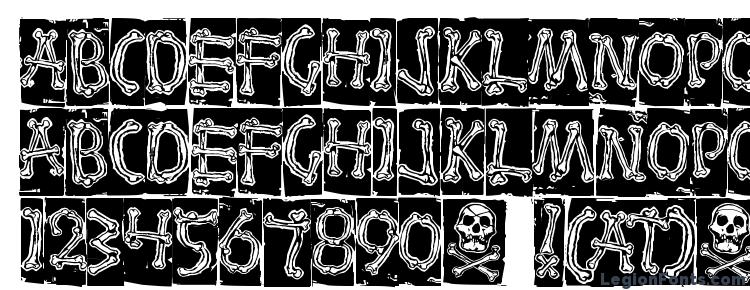
Пиратский шрифт русский: Русские шрифты | Шрифты онлайн
Журнал «Шрифт» • 10 шрифтов Владимира Ефимова
6 мая исполнилось 70 лет со дня рождения шрифтового дизайнера Владимира Ефимова (*6 мая 1949 †23 февраля 2012). Мы выбрали 10 шрифтов Владимира Венедиктовича и сопроводили их комментариями, которые он записал в 2010 году для выставки «Шрифтовых дел мастер» в Музее архитектуры. Позже они были помещены в небольшом каталоге, выпущенном компанией ParaType. Мы публикуем комментарии с небольшими сокращениями. Список начинается со шрифтов, которые не всегда связывались в сознании читателей с «академическим» стилем Владимира Ефимова. Между тем его кириллизации шрифтов Джонатана Барнбрука, студии «Эмигре» и других прогрессивных в 90-е годы словолитен и сегодня остаются мастерскими и смелыми проектами, о которых мы считаем нужным напомнить.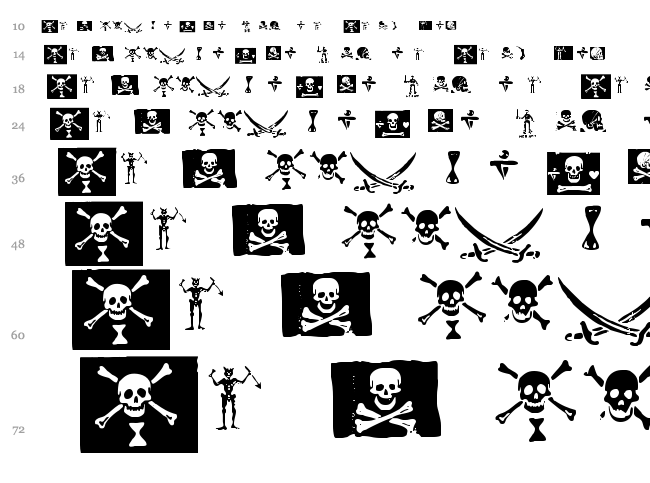
☛ ITC Avant Garde Gothic
Владимир Ефимов: «Авангард Готик — главный шрифт ITC, которым они безумно гордились. До того, как мы начали официальную работу над этим шрифтом, Максим Жуков уже заставлял меня рисовать eгo варианты для разных языков. Издательство „Мир“ выпускало литературу на русском и иностранных языках. Часть этих языков была восточная. Были издания для Индии, Афганистана и других стран. А поскольку я работал в лаборатории шрифтов особых графических форм, я был связан с восточными шрифтами. И Максим мне заказывал надписи в стиле Авангарда для индийской письменности деванагари, греческие, арабские.
У меня с этим Авангардом были уже какие-то личные отношения — он мне снился ночами. Я начал думать, как мне от него избавиться. Но тут открылся „Параграф“, и я туда перешёл, так как в отделе наборных шрифтов всё закончилось и закрылось.
У Любалина было в Авангарде нарисовано много лигатур, он хотел на новом уровне повторить то, что когда-то сделал Гутенберг. И мы решили, что раз уж выпускаем комплект начертаний в формате OpenТуре, то надо воспользоваться его преимуществом и добавить туда много-много лигатур. Мы сделали все лигатуры, которые нарисовал Любалин, а потом были сделаны кириллические аналоги, и получилось их очень много! Правда, я не знаю, зачем это нужно, но мало ли, вдруг кому-нибудь понадобится».
☛ Mason Sans
Владимир Ефимов: «Это был заказ известной пивной компании „Стелла Артуа“. У них был разработан фирменный стиль на основе Масона, и когда они открывали свое производство и представительство в России, им понадобился кириллический Масон.
Они заказали сетевому агентству разработку фирменного стиля, а те сами не стали делать кириллическую версию шрифта, а обратились к нам. Мне пришлось некоторое время этим заниматься. Этот шрифт позволяет проделывать с ним всякие модификации. Мне было довольно интересно с ним возиться: он настолько дик по своему основному решению в латинице, что мне нужно было найти ту же степень дикости в кириллице. У буквы А, например, было два варианта: одна — нормальная, треугольная (не очень нормальная, но почти), а у другой круглые бока и острая вершина, получается как будто боеголовка или снаряд. Это называется „оживальная форма“. Я сделал такие варианты ещё для Л и Д…
Когда я принёс уже довольно продвинутую нарисованную версию Масона нашему заказчику для утверждения, он, человек довольно молодой и на вид интеллигентный, сказал: вот какие шрифты были в рыцарские времена.
Тут я перепугался и сказал, что в рыцарские времена вообще-то готика была, а эта эклектика к рыцарским временам никакого отношения не имеет. В общем, мы друг друга поняли».
☛ Raleigh
Владимир Ефимов: «Был в Англии, в эпоху королевы Елизаветы, известный человек — Уолтер Рэлей (или Рейли). Фаворит королевы, личность замечательная, как и многие деятели шекспировских времён. Он был поэт и пират, организовывал экспедиции в Америку, воевал, писал историю Рима, сидя
в тюрьме в Тауэре. И, кстати, знаменит он настолько, что до сих пор в Тауэре его камера сохраняется в качестве музея — камера из двух комнат с балконом, там в общем-то неплохо было жить… Он был одним из лучших представителей эпохи королевы Елизаветы. Кончил он, правда, плохо — ему отрубили голову за государственную измену, в которой он был никак не повинен.
История этого шрифта достаточно запутанная, и сначала назывался он совершенно не так. Это был фирменный шрифт для Всемирной выставки 1969 года в Монреале, в Канаде, в одном начертании, и создал его дизайнер Карп Дэйр. Потом на его основе был сделан шрифт в двух начертаниях (прямое и курсив), названный Cartier. И опять же, я не уверен, что это было сделано по заказу этой самой знаменитой ювелирной фирмы. Его курсив был создан на основе старых и очень редких каллиграфических почерков, но в первоначальном шрифте, который был сделан для Всемирной выставки, курсива вообще не было, он был дорисован позже. Спустя какое-то время, в 1977 году, английский дизайнер Роберт Нортон на основе Cartier разработал этот самый шрифт в нескольких начертаниях — от сверхсветлого до сверхжирного.
☛ English 157
Владимир Ефимов: «Классический рукописный шрифт начала XIX века, называемый английским, или спенсерианским. В первом классе школы письму похожим шрифтом меня обучали на уроках чистописания. Мы писали металлическими перьями, макали их в чернильницу, все ходили в кляксах. Меня так и не научили толком. Пишутся они остроконечным стальным пером, позволяющим усиливать нажим, что делает их контрастными рукописными шрифтами, которые гармонировали с модными тогда Дидо и Бодони. Это имитация наборным способом рукописных шрифтов. English 157 — шрифт полусвязный: у него есть выходящие концы штрихов, а входящих концов нет. В основе его лежит знаменитый каллиграфический шрифт немецкого происхождения под названием Englische Schreibschrift („Английский рукописный шрифт“).
Я выбрал eгo сознательно, чтобы сделать кириллическую версию: такого типа шрифтов у нас не было, или были не очень качественные, с моей точки зрения.
☛ Kuenstler 480
Владимир Ефимов: «В 80-е годы в издательстве „Мир“ главным художником был Максим Жуков, и он пригласил меня делать разные шрифтовые работы. Мы делали книгу, которую заказала Ассоциация участников космических полётов. Это сборник космических фотографий удивительной красоты. Называлась она „Наш дом — Земля“. Это был перевод американского издания, и шрифт должен был быть как в оригинале. С текстовыми шрифтами это было тогда невозможно. Это сейчас их много, а тогда имелись только Таймс и Гельветика, гарнитура Литературная как-то не подходила. Но хотя бы переплёт и титул должны были соответствовать оригиналу. И мне заказали такую вот работу.
Владимир Ефимов о работе над кириллической версией шрифта Kuenstler 480. 2010 год.
Некоторое время у меня ушло на то, чтобы опознать шрифт, так как там нигде не было написано его названия. Потом я его нашёл в каталоге, оказалось, что это Трамп Медиеваль. Я его переснял с увеличением, перерисовал на кальку. Никто не знал, прописными нужно было делать надпись или строчными, поэтому я сделал и то и другое. Это был первый вариант шрифта, и он потом никуда не пошёл. Современный вариант я сделал уже позже в „ПараТайпе“ на основе цифровой битстримовской версии».
☛ ImagoВладимир Ефимов
: «Гюнтер Герард Ланге разработал для Бертольда множество шрифтов — варианты классических гарнитур, перерисованные для фотонабора, и оригинальные.
Imago — его оригинальный шрифт. Изначально он был разработан в меньшем количестве начертаний, но в 2000 году в Чикаго было сделано жирное начертание, в 2005 году — нормальное, которого в оригинальном фотонаборном шрифте не было. В результате гарнитура получилась естественно возрастающей по насыщенности, без рывков от светлых начертаний к жирным.В каждом начертании этой гарнитуры есть капитель, что для меня было довольно странно. Не очень понимаю, зачем нужна капитель в гротеске, особенно в наклонных начертаниях. Однако теперь в шрифтовом дизайне принято давать типографу как можно больше возможностей, а уж воспользуется он ими или нет — это его дело».
☛ Octava
Первоначальная русская версия в трёх начертаниях под названием Scriptura Rossicа (1996) была заказана Российским библейским сообществом.
Владимир Ефимов: «Эскизы шрифта были показаны в библейском сообществе для утверждения, после чего в каждом начертании были доработаны недостающие знаки и построены рабочие файлы шрифта.
Они были переданы заказчику, который провёл своё тестирование в условиях вёрстки реального издания. Несколько полос из Библии были набраны новым шрифтом с разными установками: разными кеглями, при различных значениях интерлиньяжа, комбинациях начертаний и т. д. После последних корректировок и технической обработки всех знаков (хинтования) шрифт был построен уже в окончательной версии и передан заказчику».
☛ Гарнитура Лазурского
Владимир Ефимов: «Как пишет сам Лазурский в своих воспоминаниях, eгo работа над наборным шрифтом началась в 1957 году в Отделе редких книг Библиотеки им. Ленина (сейчас Российская государственная библиотека), где он вручную копировал латинские шрифты эпохи Возрождения. На основе этого материала он затем стал искать форму знаков будущей гарнитуры Лазурского. К сожалению, Лазурский не оставил подробного описания этапов этого процесса.
По иллюстрациям, помещённым в его книге, видно, как от прилежных карандашных копий исторических образцов он перешёл к рисованию собственных буквенных форм.
Эскизы Вадима Лазурского к первому типографскому шрифту, позже названному гарнитурой Лазурского. 1957. Из мемуаров художника „Путь к книге“ (М.: Книга, 1985).
Среди множества эскизов этого периода есть несколько рисунков, свидетельствующих о том, как художник, вынужденный по техническим требованиям перейти к резко увеличенному масштабу букв, должен был определить стиль и форму будущих наборных знаков. Эти рисунки букв поражают своей удивительной экспрессией и современностью: увеличенные копии отпечатков текстовых шрифтов, с присущим им ростиском краски и погрешностями ручного рисования, в крупном размере приобрели неожиданные графические качества. За их внешней суровостью чувствуется железная конструкция и пятисотлетняя традиция шрифтового дизайна.
Именно так и должен выглядеть в таком размере настоящий текстовый шрифт, и первая аналогия, приходящая в голову при виде этих эскизов, — это шрифты Уильяма Двиггинса, а также шрифт IТС Galliard Мэтью Картера, который опирался на шрифты Робера Гранжона».
☛ Didona
Владимир Ефимов: «Для книги Максима Жукова про Большой театр я сделал эскизы. Но затем они долго лежали без движения. Потом мне стало обидно, что они лежат, и захотелось их использовать. Но когда я собрался делать нормальный шрифт, я понял, что шрифт такой контрастности и с такими немного диковатыми формами у нас никто не выдержит. И тогда я волевым решением взял и увеличил вдвое толщины тонких штрихов, то есть в эскизах толщина штриха была 1 мм, а стала 2 мм. И из этого тогда получился шрифт Дидона.
Владимир Ефимов о том, как делался шрифт Дидона.
2010 год.
В сущности, это не просто шрифт, а моё отношение к шрифту в те времена. И не просто отношение, а отношение довольно ехидное. Там есть некоторые вещи, которые „я себе позволил“. Вот, например, 4 и 7 — это реально существующие цифры, они подсмотрены и срисованы, но вот такой Д тогда ещё ни у кого не было. Или капля у буквы З — в этих знаках, формах есть внутреннее ехидство, это не просто переработка известной формы, а моё личное, немного ироничное отношение к ним, здесь есть элемент игры. В нормальном шрифте я бы такого не сделал, то есть сделал бы, но немного не так, а более серьёзно».
☛ Kis
Владимир Ефимов: «Матрицы этого шрифта были найдены в начале ХХ века, тогда же был отлит с этих матриц шрифт. Сначала его авторство приписывали Антону Янсону, но только в 50-е годы ХХ века обнаружили, что это Николай Киш. Я давно на него смотрел, и мне, конечно, хотелось сделать кириллическую
версию, потому что, по-моему, это один из самых красивых латинских шрифтов.
Я попробовал его рисовать, получилось, конечно же, не сразу. Уже в современные времена „ПараТайп“ заключил договор с американской фирмой Bitstream, по которому мы имеем право делать кириллические версии их шрифтов. А у них в библиотеке был шрифт Киш, и поскольку я уже давно начал его рисовать, то эта работа досталась мне.
Владимир Ефимов о разработке кириллической версии шрифта Kis. 2010 год.
Это было связано ещё с тем, что я всегда не понимал Петровскую реформу, гражданский шрифт, который получился такой достаточно странный, и я решил, что надо было взять самый лучший латинский шрифт и уже к нему подбирать варианты кириллических знаков. И я выбрал шрифт Киш, так сказать, для повторения Петровской реформы на современном уровне, чтобы сделать формы наших букв более человеческими».
Создателей мультика My Little Pony судят за пиратский шрифт / Хабр
Компания-разработчик шрифтов Font Brothers подала в суд на производителя игрушек и настольных игр Hasbro за использование одного из фирменных шрифтов без разрешения. Согласно жалобе Font Brothers, компания Hasbro отказалась платить лицензионные отчисления и продолжала использовать шрифт в товарах линейки My Little Pony (в русском переводе мультик называется «Дружба — это чудо»).Конфликт возник из-за шрифта Generation B, который создал дизайнер Гарольд Лонер (Harold Lohner). В судебном иске (pdf) сказано, что шрифт использовался в линейке игрушек и сувениров My Little Pony, а также в мультсериале и рекламных материалах Hasbro, чему есть доказательства. К исковому заявлению прилагаются образцы буклетов и фотографии игрушек с контрафактным шрифтом.
Доказательства довольно убедительные, тем более что в исходном коде HTML-страниц на веб-сайте Hasbro прямо указано использование шрифта Generation B.
Неизвестно, почему Hasbro отказалась покупать лицензию на использование шрифта. Возможно, запрошенная сумма оказалась слишком высокой.
По оценке экспертов, потенциальный ущерб Font Brothers может составить миллионы долларов. Вдобавок, Font Brothers имеет право потребовать уничтожения всех товаров и материалов, где используется пиратский шрифт.
События в мультфильме My Little Pony разворачиваются в вымышленной стране Эквестрия, населённой пони. Главная героиня — единорог по имени Сумеречная Искорка (Twilight Sparkle), которая целые дни проводит за книгами, не уделяя ни минуты общению с другими пони. Её наставница принцесса Селестия даёт ей задание — найти настоящих друзей. Героиня и её помощник дракончик Спайк отправляются в Понивиль, где встречают преданную друзьям Радугу Дэш, щедрую Рарити, честную Эпплджек, добрую Флаттершай и всегда веселую Пинки Пай.
Целевая аудитория мультсериала — девочки от 4 до 7 лет.
Слева направо: Пинки Пай, Рарити, Радуга Дэш, Сумеречная Искорка, Эпплджек и Флаттершай
Тара Стронг, Сумеречная Искорка
Получается, что маленькие девочки 4-7 лет, которые смотрят мультсериал и покупают игрушки с пони, тоже пользуются пиратской продукцией.
Шрифт и контент | Блог Смартпринт.рф
Часто текст расценивают, как контент (смыслы) и забывают о его роли, как о графическом элементе (выбор шрифта). А между тем, шрифт воздействует на подсознание не меньше, чем цвет (следовательно, и на восприятие рекламного материала).
Сила смыслов должна быть подкреплена силой визуализации
Вопросы, которые возникают при работе с шрифтами:
- Как выбрать шрифт?
- Какие параметры необходимо учитывать, чтобы подобрать шрифт для макета?
- Где найти бесплатные шрифты?
Шрифт — инструментом визуальной коммуникации бренда с потребителем.
Каждый шрифт имеет свое воздействие на подсознание, задает настроение во время чтения текста.
Прямые вытянутые шрифты отлично подходят для рекламы услуг и продукции, где нужно передать деловое настроение, но не уместны для необычных, уникальных товаров, которым нужно выделиться на фоне конкурентов.
Строгие квадратные шрифты призваны настроить человека на серьезность предоставленной информации.
Где используют:
- реклама промышленных товаров,
- продвижение технологий,
- для социальной рекламы.
Округлые шрифты передают чувство комфорта и уюта. Ассоциируются с добрым отношением бренда к потребителям.
Если у продукта основная аудитория девушки и женщины, то лучше использовать наклонные шрифты, они ассоциируются с легкостью и красотой.
Где используют: салоны красоты, магазины одежды, косметические бренды.
Рукописные шрифты — это попытка передать дружелюбие и близкие отношения.
Такие шрифты вызывают чувство доверия и придают большую достоверность информации.
Где используют:
- дизайн для адвокатских и консалтинговых услуг,
- реклама врачебной практики,
- для пригласительных,
- при проведении политических PR-акций.
На шрифты часто не обращают внимания. У нас на Смартпринт был случай, когда после масштабирования макета из формата А4 до формата до А5 некоторые текстовые элементы наехали друг на друга.
Мы предложили заказчику доработать макет или отправить специалисту допечатной подготовки шрифт, который использован в файле. На это заказчик ответил: «Поставьте там какой-нибудь свой шрифт, мне главное, чтобы смысл не изменился.
Этот пример очень хорошо демонстрирует отношение к шрифту.
Давайте разбираться, чем шрифты отличаются и для каких целей подходят.
Есть две основные группы шрифтов — антиквы и гротески. Антиквы — это шрифты с засечками, гротески — без засечек.![]()
Для длинных текстов лучше использовать шрифт с засечками. Так текст будет легче читать.
Шрифты без засечек, то есть гротески, окружают нас повсюду — они используются в логотипах, рекламе, упаковке и даже в книгах.
При подборе шрифта важно руководствоваться не только аргументом «нравится/не нравится», но и учитывать сферу деятельности. Нельзя использовать один и тот же шрифт и для рекламы детских товаров, и для продвижения услуг юридической фирмы.
Отдельная тема — сложные/необычные шрифты, они хороши для названий заголовков, но не для основного текста, иначе он просто станет не читаемым.
Каждый шрифт был сделан для решения определенной задачи, это стоит учитывать при его использовании.
При выборе шрифта нужно брать во внимание контекст. Не используйте готические шрифты для рекламы пекарни, а славянскую вязь — для логотипа фитнес-клуба.
Есть платные и бесплатные шрифты. Для крупного проекта есть смысл заморочиться на покупку или даже на разработку шрифтовой гарнитуры специально под ваш проект, но если вам нужно подобрать шрифты для брошюры или буклета, то можно воспользоваться бесплатными вариантами.
Бесплатный, не значит пиратский.
Это может быть просто бесплатный шрифт, работа начинающего шрифтовика или любителя, акция в магазине или пробная версия.
Где искать бесплатные шрифты:
Free Design : Отборные Бесплатные Шрифты
BaseFonts. Отборные кириллические шрифты
- Студии, разрабатывающие шрифты
На своих сайтах они продают шрифты собственного производства, но, кроме этого, часто можно найти 1-2 бесплатных шрифта, например:
Russianfonts
Typefaces of the temporary state
Free Fonts Project
Fontfabric
У многих платных шрифтов часто есть 1-4 бесплатных начертания.
- Отдельные дизайнеры
- Сайты с подборками
Вариант удобен тем, что в нём уже собраны многие шрифты из предыдущих пунктов в одном месте. Но есть и минус: в подобных подборках могут быть и пиратские шрифты.
https://graphicsland.ru/mark/cyrillic/
https://shriftkrasivo.
ru/category/cyrillic/. - Поиск на Behance
Достаточно ввести в поиск «Cyrillic free» и посмотреть варианты.
Похожие статьи:
Шрифт как элемент фирменного стиля
Принимая во внимание деятельность фирмы ParaType, разговор пойдет преимущественно о шрифтах. Очень хочется думать, что читатели понимают, что шрифт появляется не «с дискетки». Его делают художники, поэтому как и любое произведение искусства, будь то графический дизайн или фотография, шрифт является авторским произведением.
Начнем с простых примеров того, как различные фирмы подходят к решению вопросов поддержания единого фирменного стиля и ситуаций, в которые в связи с этим попадают отечественные фирмы и представительства иностранных компаний в России.
Первым хотелось бы упомянуть Сбербанк Российской Федерации, который использует хорошо узнаваемый всеми нашими гражданами шрифт ITC Benguiat (назван по фамилии автора). Слова «Сберегательный банк» на всех бланках, буклетах, сберкассах на всевозможных языках написаны этим шрифтом.
Долгое время Сбербанк использовал нелегальную русифицированную версию этого шрифта.
Под «нелегальной версией» в данном случае подразумевается следующее: с пиратского диска берется шрифт, содержащий символы латиницы. Некий «местный дизайнер» дорисовывает кириллические символы, не согласуя работу с владельцем оригинала. Полученный таким образом шрифт получает широкое распространение на тех же пиратских дисках. И вот некое рекламное агентство или дизайн-бюро разрабатывает фирменный стиль, не обращая внимание на происхождение шрифта. Шрифт становится фирменным и используется в логотипе. Тем самым наносится серьезный урон репутации клиента, так как хоть и существует техническая возможность тиражировать шрифты, представленные в компьютерных форматах, это не отменяет необходимость соблюдения Закона РФ «Об авторском праве и смежных правах».
И вот в Сбербанке, спустя какое-то время, возникла необходимость проверить все элементы фирменного стиля с точки зрения соблюдения авторских прав.
Нужно было сделать следующее: первое — приобрести право использовать латинскую часть шрифта, второе — русифицировать в России латиницу, то есть, создать кириллицу. И третье — приобрести лицензии на установку шрифта на определенном количестве (более ста) компьютеров для работы во всех филиалах.
Второй пример. Американская фирма Compaq (один из лидеров компьютерного мира), имеющая свой фирменный стиль, обязала сотрудников российского офиса оформлять документацию на русском языке в соответствии с системой корпоративной идентификации. В эту систему входил шрифт Тезис (автор Лукас де Грот, довольно известный немецкий дизайнер). Фирма имела права на латиницу. Была создана кириллица и приобретена простая лицензия на использование кириллицы для издательской деятельности и выпуска техдокументации.
Третий пример.* Концерн Фольксваген на билбордах и в печатной рекламе автомобиля VW (не Аudi) использовала шрифт Futuris Demi. Можно сравнить журналы для западного читателя и российского: тексты в них набраны разными шрифтами.
В западных изданиях используются шрифты VAG Rounded (фирменный шрифт Фольксвагена) и Futura.
Не найдя похожего на VAG Rounded кириллического шрифта, компания просто исключила его из рекламы, а вместо Futura использовала ближайший аналог — шрифт Futuris. Оба действия вызывают удивление, т.к. в масштабах рекламной кампании автомобильной фирмы изготовить любой фирменный шрифт на заказ вполне реальная задача, что же касается шрифта Futura, то существуют официальные кириллические версии этой гарнитуры, созданные фирмой ПараТайп.
Первый случай, пожалуй, наиболее общий и наиболее серьезный. Речь идет о большой организации с развитой системой филиалов, с достаточно жесткими требованиями к системе корпоративной идентификации. Для банка фирменный стиль играет особую роль. Надпись «Сбербанк Российской Федерации» должна быть едина для всех документов и для всех филиалов, как в России, так и за рубежом.
Второй случай с переводом фирменной документации на другие языки — более частный, но не менее интересный.
Обратите внимание на то, что в паспортах бытовой техники, выпущенной 3-5 лет назад, уже переведенных на русский язык (это может быть 10 языков), все блоки набраны разными шрифтами: латиница одним, кириллица другим, иная группа языков — третьим. Если же вы возьмете современную техническую документацию солидной фирмы, то все чаще и чаще весь документ оформлен в едином формате, набран единым шрифтом на всех языках и имеет некий унифицированный вид. Для системы корпоративной идентификации это, безусловно, имеет значение.
Третий случай интересен как пример международной рекламной кампании, проводимой сетевыми агентствами. Он аналогичен первому и второму, является массовым, но «работает» в период проведения конкретной рекламной кампании. Если рекламная кампания имеет интернациональный характер, очень важно для сохранения визуального ряда использовать в разных странах, для разных языков, один и тот же набор шрифтов. В компании Мерседес данное требование выполняется повсеместно. Вся реклама Мерседеса сверстана c использованием одного шрифта, и в телефонных справочниках, и в журналах.
Можно привести примеры использования фирменного шрифта транснациональными табачными компаниями или фирмами, торгующими продуктами питания. Однако, в подавляющем большинстве случаев, на территории бывшего СССР фирменный стиль в рекламных кампаниях не соблюдается. Макеты рекламы сохраняют слоган, логотип и видеоряд, но, к сожалению, шрифт подбирают по критерию «похож — не похож», что говорит о недостаточной профессиональной подготовке сотрудников рекламных агентств. Подобные решения должны принимать профессионалы, так как каждый шрифт соответствует вполне определенному стилю и направлению в графическом дизайне, и даже «маленькая» ошибка может полностью разрушить первоначальную идею оригинального дизайна. «Специалистам», которые считают, что все шрифты одинаковы, напомню, что для европейца все китайцы имеют одинаковое выражение лица и абсолютно похожи друг на друга.
Когда мы говорим о фирменном стиле или о системе корпоративной идентификации, то имеем в виду целый комплекс понятий. И шрифт является одной из составляющих, наравне с сеткой, фирменным цветом, логотипом.
Какие трудности нас здесь ждут?
Начнем с чисто технологических. Международные рекламные кампании, как правило, приходят к нам с запада. На западе коммерческих шрифтов (по каталогам) более 15 тысяч. Причем, западные фирмы, наверное, не зря тратят такие большие деньги на рекламу и консультантов. Очень часто они используют модные шрифты, которые появились 2-3 года назад, и существуют, как правило, только в латинице. Это большая проблема для нашего рынка. Не только потому, что необходимо подбирать кириллицу. В российских регионах такая реклама идет на национальных языках, и очень часто проблема белорусского, украинского, татарского, казахского языка — это проблема московского рекламного агентства. И надо обращать на это внимание. Если не получается сделать «как в латинице», надо постараться подобрать близкий шрифт. Здесь очень важно обратиться к специалисту, профессионалу.
К примеру, шрифт, используемый в рекламной кампании «Ингосстраха», существует для украинского и большинства других языков.
Но при проведении рекламной кампании по России в целом, местные рекламисты в Башкирии и Татарстане вряд ли обратят внимание на то, что шрифт именно Futuris, а не Helvetica, Pragmatica или Arial. На это обязательно должен обратить внимание менеджер, составляя контракт. Подрядчику фирменный цвет, набор фотографий, текст, шрифт должны передаваться единым комплектом. Эти требования должны быть изложены соответствующим образом по всей цепочке договоров.
Здесь могут быть совершенно неожиданные и чисто утилитарные проблемы. Если шрифт заменен на похожий, может просто не сохраниться верстка при фотонаборе. При замене одного шрифта другим, текст просто «сползет» (если речь идет о десяти символах) или будет переверстан (если о нескольких предложениях). У другого шрифта другая ширина, другая высота символа. И возможно, что если и не будет утерян смысл, то некий замысел, задуманный дизайнером, вполне может быть нарушен.
Сегодня в рекламе товаров народного потребления, автомобилей, продуктов питания и т.
д., как правило, стараются избегать характерных шрифтов, если они не являются частью товарного знака. Пример — тот же, достаточно нейтральный, Futura в рекламе Фольксвагена. Современный, конструктивистский, он был моден в начале 80-х и широко используется в настоящее время. Решение, позволяющее сделать замену,если нет прямого аналога шрифта. Очень часто западная реклама (я обращаю внимание на то, что это один из критериев высочайшего профессионализма дизайнера) сделана так, что шрифт можно заменить другим без потери смысла и задумки дизайнера. Ну, будет не так красиво. Да, профессионалы заметят. Но это вполне допустимо. Дизайн шрифта может не нести смысловой нагрузки, если он не привязан к изображению временем, дизайном, стилем и т.д.
Здесь есть минусы. Говорят, интернациональные рекламы безлики, в них нет «изюминки». Но они очень профессиональны, их сложно испортить. Это удобно для рекламы автомобилей, магнитофонов, жвачки, напитков. Для системы корпоративной идентификации ситуация прямо противоположная — шрифт должен нести смысловую нагрузку.
Речь идет, прежде всего, о годовых отчетах и иной документации банков, страховых компаний, других финансовых организаций.
Если ваша задача — узнавание компании, создание некоего образа в документах: отчетах, бланках, визитных карточках, то самый важный принцип — соблюдение меры. В «серьезной» документации шрифт, когда шрифт несет еще и содержательную функцию, как правило, используют шрифты, которые ассоциируются с богатством, респектабельностью, например, классические шрифты типа Garamond или Baskerville. Это действительно солидные шрифты, перед которыми хочется снять шляпу. Они очень непросты в использовании и выдвигают дополнительные требования к дизайну в целом. Это требует от автора дизайн-проекта дополнительных знаний по истории и типографике. Но, может быть, эти шрифты правильнее использовать в альбомах по искусству?
В архитектуре количество золота, лепнины, резной фасад — признак определенной эпохи, стиля. И если уж вы построили екатерининский дворец, то и ходите в парике и парче. А если уж приехали на современном спортивном автомобиле и у вас особняк из финских материалов, то и шрифт лучше не екатерининской эпохи взять, а современный, чуть агрессивный, что не мешает ему быть модным и респектабельным. Большинство ошибок современного полиграфического дизайна как раз связано с полным несоответствием выбранного шрифта характеру и содержанию издания.
Трудно соблюсти всю линию фирменного стиля, включая интерьер помещений и униформу сотрудников. Необходимо выдерживать в стиле все элементы, включая и цветовую гамму.
И еще архитектурный пример — С.-Петербург. Желтые здания имеют дизайн своего времени. Зеленоватые — своего. Их не перекрасишь. Если вы построили особняк и покрасили его в голубой цвет — делайте лепнину. А если стиль более конструктивистский, хотите Смольный, — покрасьте его в желтый цвет.
Наверное, не нужно подстраивать весь фирменный стиль под здание, в котором работаешь, но иметь в виду простейшие правила необходимо. Ведь очень странно смотрится шрифт стиля модерн (первой половины 20 века) на екатерининском особняке. Если речь идет о вывеске «Трактир» или «Пивная», то с этим еще можно смериться, но если о наименовании банка либо представительства некоей западной компании, — то это вызывает улыбку. К тому же часто в рекламе используется вид главного офиса компании. И стиль рекламы, в этом случае, должен соответствовать парадному подъезду. Вывеска — архитектуре подъезда.
Не нужно быть профессором графики или преподавать оформление книги, чтобы понимать: шрифт, если он используется в наружной рекламе — это такая же часть среды, как и архитектура. Если же он используется на бумаге, то это такой же равноправный элемент, как все остальное, что помещено на этой же странице.
Если об этом помнить и стараться привести все компоненты в соответствие, то сам собой выстроиться стиль. Если он не выстраивается или что-то не получается, значит, надо что-то изменить. Как правило, шрифт поменять легче, чем все остальное. Если уже существует фотография президента в рыцарских доспехах, то ничего с ней поделать нельзя (как в прямом, так и в переносном смысле). И если миллионы уже затрачены на реконструкцию подъезда в первозданном виде. Шрифт является, как правило, менее критичной частью.
Не надо бояться современных шрифтов, современного дизайна. Только важно соблюсти в фирменном стиле некую преемственность и сбалансированность звучания. Я видел хорошие фирменные стили, построенные на швейцарской типографике: Гельветика и т.п. — все очень строго. Это не очень модно, не очень современно. Сейчас так не делают. Но если это было сделано в свое время продуманно, то здесь есть и преимущества: фирменный стиль показывает, когда он был создан и как долго существует. Он служит дополнительным фактором в выполнении поставленной задачи — отразить, например, незыблемость и надежность банка.
Одна компания может использовать несколько шрифтов с разными целями: один — для официальных документов, нормированный, гостированный. Другой может быть массово тиражируем, им можно печатать техническую документацию. Третий может представлять собой комплект для текущей рекламной кампании. Шрифты не обязательно должны быть сверхмодными и выдающимися. Они должны соответствовать поставленной задаче.
На западе фирменные шрифты имеют не только солидные компании, но и у государственные департаменты. Заказные шрифты есть у газет, которые стараются идентифицировать себя в общем поле. Для коммерции очень важно, когда в огромном развале газет можно мгновенно отличить то или иное издание по заголовку, по набору, не будучи специалистом. Нам до этого далеко. Но к использованию уникального заказного шрифта, как элемента фирменного стиля, мы приходим. Пример тому — Сбербанк. Многие просят изменить в шрифте несколько букв, чтобы стиль стал фирменным, и его можно было идентифицировать.
Есть хорошие примеры того, как надо работать со шрифтами. «Коммерсант Дейли» несколько раз менял шрифт. Поиск был достаточно длительным. Подзаголовки сейчас набираются фирменным шрифтом Free Set — аналогом шрифта Frutiger «живого классика» типографики Андриана Фрутигера. Это современный открытый гротеск, очень хорошая альтернатива Гельветики. Хотя есть уже новые гротески, он останется современным еще лет десять-двадцать. В качестве заголовочного шрифта используется Swift (это антиква с тяжелыми рублеными засечками, автор Унгер). Нигде больше как в «Коммерсант Дейли» он не используется. Сейчас делается новая версия Swift, который будет массово тиражироваться и продаваться всем желающим.
Еще один, на этот раз вопиющий пример. Замечательная, своевременная акция «Знак рубля». Молодцы! Сто баллов! Конкурс проводили профессиональные журналисты, дизайнеры. Но почему в отборочной комиссии не было ни одного шрифтовика? Из Академии печати, из Союза дизайнеров, откуда угодно. Из-за границы, наконец. В числе выбранных знаков есть буква «Ъ» из гарнитуры Лазурского. Поскольку знак рубля — шрифтовой знак (как доллар, как иена, фунт), получается, что твердый знак гарнитуры Лазурского нужно вставить во все существующие шрифты. Понятно, что знак рубля будет использоваться вместе с цифрами, что его нужно поставить во все, имеющие хождение шрифты. Этот знак рубля будет рисоваться для гротеска, антиквы, декоративного шрифта. Он должен соотноситься со знаком иены, доллара, форинта, флорина, и др. Только один знак из вышедших в финал сделан профессионально, дизайнером-шрифтовиком. Остальных «врачи не лечили».
Хороших справочников на русском языке, где есть обзоры шрифтов, нет, зато есть десятки на английском, Это любая книга по типографике (одной из лучших я считаю книгу Эмиля Рудера «Типографика»). Но в то же время компетентные грамотные люди, профессионально занимающиеся рекламой, не пытаются самостоятельно выводить пленки. Они идут в фотонаборный центр и консультируются, какой должна быть верстка, чтобы она была технологична и хорошо выводилась на фотонаборе. Они консультируются с представителями типографий, какой должен быть цвет, чтобы он хорошо напечатался и на мелованной бумаге, и на простой офсетной. То же самое со шрифтом. Не надо бояться проконсультироваться. Есть очень хорошие дизайнеры, которые в этом разбираются. Есть просто художники-шрифтовики. Есть преподаватели в полиграфическом институте. Этих людей немало. Их несложно найти. Любой профессиональный дизайнер-полиграфист скажет вам, что дизайн шрифта — это «высший пилотаж».
Можно сколь угодно долго рассказывать о правилах построения кириллицы, это целый мир. Но лучше, если вам поможет человек, который этим занимается профессионально. Если вам не понравился один консультант, идите к другому, это легче, чем с врачом. Но если и второй, и третий говорят одно и то же, нужно задать себе вопрос: а прав ли я?
По информации dp-foto.ru
Автор:
☠ — Череп и кости Эмоджи: U+2620
пиратский флаг, смерть, опасность
U+2620
Emoji
Отображение этого Emoji в разных системах
Значение Эмоджи
Череп с двумя скрещёнными костями означает смерть или смертельную угрозу. Такой символ предупреждает о минном поле или химическом заражении. Пираты рисовали нечто подобное на своём флаге и называли его «весёлый Роджер».
Символ «Череп и кости» был утвержден как часть Юникода версии 1.1 в 1993 г. и был добавлен в Эмоджи версии 1.0 в 2015 г.
Этот текст также доступен на следующих языках: English;
Свойства
| Версия | 1.1 |
| Блок | Разные символы |
| Тип парной зеркальной скобки (bidi) | Нет |
| Композиционное исключение | Нет |
| Изменение регистра | 2620 |
| Простое изменение регистра | 2620 |
Злое или недовольное лицо
Кодировка
| Кодировка | hex | dec (bytes) | dec | binary |
|---|---|---|---|---|
| UTF-8 | E2 98 A0 | 226 152 160 | 14850208 | 11100010 10011000 10100000 |
| UTF-16BE | 26 20 | 38 32 | 9760 | 00100110 00100000 |
| UTF-16LE | 20 26 | 32 38 | 8230 | 00100000 00100110 |
| UTF-32BE | 00 00 26 20 | 0 0 38 32 | 9760 | 00000000 00000000 00100110 00100000 |
| UTF-32LE | 20 26 00 00 | 32 38 0 0 | 539361280 | 00100000 00100110 00000000 00000000 |
О переводах и технических трудностях… (Выпуск 1) — Офтоп на DTF
Судя по результатам первого-последнего выпуска, вам понравилось, дорогая аудитория. Ну-с, как и обещал, мы начнём по порядку.
Небольшой дисклеймер: не удивляйтесь разнице в структуре и стиле. Всё же выпуски первые и я только начинал экспериментировать. А теперь — приятного чтения!
P.S. Данный выпуск был опубликован впервые 25-го мая 2017-го.
{«id»:13880,»url»:»https:\/\/dtf.ru\/flood\/13880-o-perevodah-i-tehnicheskih-trudnostyah-vypusk-1″,»title»:»\u041e \u043f\u0435\u0440\u0435\u0432\u043e\u0434\u0430\u0445 \u0438 \u0442\u0435\u0445\u043d\u0438\u0447\u0435\u0441\u043a\u0438\u0445 \u0442\u0440\u0443\u0434\u043d\u043e\u0441\u0442\u044f\u0445\u2026 (\u0412\u044b\u043f\u0443\u0441\u043a 1)»,»services»:{«vkontakte»:{«url»:»https:\/\/vk.com\/share.php?url=https:\/\/dtf.ru\/flood\/13880-o-perevodah-i-tehnicheskih-trudnostyah-vypusk-1&title=\u041e \u043f\u0435\u0440\u0435\u0432\u043e\u0434\u0430\u0445 \u0438 \u0442\u0435\u0445\u043d\u0438\u0447\u0435\u0441\u043a\u0438\u0445 \u0442\u0440\u0443\u0434\u043d\u043e\u0441\u0442\u044f\u0445\u2026 (\u0412\u044b\u043f\u0443\u0441\u043a 1)»,»short_name»:»VK»,»title»:»\u0412\u041a\u043e\u043d\u0442\u0430\u043a\u0442\u0435″,»width»:600,»height»:450},»facebook»:{«url»:»https:\/\/www.facebook.com\/sharer\/sharer.php?u=https:\/\/dtf.ru\/flood\/13880-o-perevodah-i-tehnicheskih-trudnostyah-vypusk-1″,»short_name»:»FB»,»title»:»Facebook»,»width»:600,»height»:450},»twitter»:{«url»:»https:\/\/twitter.com\/intent\/tweet?url=https:\/\/dtf.ru\/flood\/13880-o-perevodah-i-tehnicheskih-trudnostyah-vypusk-1&text=\u041e \u043f\u0435\u0440\u0435\u0432\u043e\u0434\u0430\u0445 \u0438 \u0442\u0435\u0445\u043d\u0438\u0447\u0435\u0441\u043a\u0438\u0445 \u0442\u0440\u0443\u0434\u043d\u043e\u0441\u0442\u044f\u0445\u2026 (\u0412\u044b\u043f\u0443\u0441\u043a 1)»,»short_name»:»TW»,»title»:»Twitter»,»width»:600,»height»:450},»telegram»:{«url»:»tg:\/\/msg_url?url=https:\/\/dtf.ru\/flood\/13880-o-perevodah-i-tehnicheskih-trudnostyah-vypusk-1&text=\u041e \u043f\u0435\u0440\u0435\u0432\u043e\u0434\u0430\u0445 \u0438 \u0442\u0435\u0445\u043d\u0438\u0447\u0435\u0441\u043a\u0438\u0445 \u0442\u0440\u0443\u0434\u043d\u043e\u0441\u0442\u044f\u0445\u2026 (\u0412\u044b\u043f\u0443\u0441\u043a 1)»,»short_name»:»TG»,»title»:»Telegram»,»width»:600,»height»:450},»odnoklassniki»:{«url»:»http:\/\/connect.ok.ru\/dk?st.cmd=WidgetSharePreview&service=odnoklassniki&st.shareUrl=https:\/\/dtf.ru\/flood\/13880-o-perevodah-i-tehnicheskih-trudnostyah-vypusk-1″,»short_name»:»OK»,»title»:»\u041e\u0434\u043d\u043e\u043a\u043b\u0430\u0441\u0441\u043d\u0438\u043a\u0438″,»width»:600,»height»:450},»email»:{«url»:»mailto:?subject=\u041e \u043f\u0435\u0440\u0435\u0432\u043e\u0434\u0430\u0445 \u0438 \u0442\u0435\u0445\u043d\u0438\u0447\u0435\u0441\u043a\u0438\u0445 \u0442\u0440\u0443\u0434\u043d\u043e\u0441\u0442\u044f\u0445\u2026 (\u0412\u044b\u043f\u0443\u0441\u043a 1)&body=https:\/\/dtf.ru\/flood\/13880-o-perevodah-i-tehnicheskih-trudnostyah-vypusk-1″,»short_name»:»Email»,»title»:»\u041e\u0442\u043f\u0440\u0430\u0432\u0438\u0442\u044c \u043d\u0430 \u043f\u043e\u0447\u0442\u0443″,»width»:600,»height»:450}},»isFavorited»:false}
Вспоминая бурную молодость и расцвет моей переводческой деятельности, не могу не отметить: по большей части они строились на одном энтузиазме. Однако сейчас, в пору занятности и отсутствия достаточного свободного времени, энтузиазм погас, но любовь к переводам не остыла. Сейчас же я готовлюсь к довольно интересному проекту, и хотелось бы поведать вам о «трудностях перевода» не в плане разница локализаций, а в плане самого процесса. В качестве примеров возьму два проекта: Resident Evil Zero (+HD Remaster) и Winx Club (2006-го).
Феечки Винкс могут задать жару…
Начнём с более простого. Игру по мультсериалу «Клуб Винкс» издала Konami в 2006-ом. Как не странно, игра было довольно неплоха. Это хороший (для игры по детскому мультфильму) экшен-платформер, где исследование сменяется платформингом, платформинг боями (Боевая система строится на уклонениях, захвате цели и стрельбе), а бои снова исследованием. Но в этой статье нас интересует не сама игра, а… «Внутренний мир» или её файлы. Я не буду разбирать сейчас версию для PS2 (Однако в ней я копался, пытаясь выудить ролики, но об этом позже). Наша цель – версия для PC. Итак. Что же нам надо искать в игре с точки зрения перевода?
Шрифт.
Это нужно смотреть и искать в первую очередь, поскольку выудить один текст недостаточно. Если вы хотите сделать качественный перевод, то придётся напрячься и вставить в шрифт русский алфавит. Если же по каким-то причинам это не получается, то некоторые одарённые личности обходятся тем методом, которые придумали пираты в 90-ые/начале нулевых – замена латиницы на русский шрифт, в результате чего текст превращался в «POMOGNTE!» при пристальному изучении файлов с текстом. Но, к счастью, Winx Club не стали привередничать и с радостью проглотили новый шрифт от товарища Thief1987, так что текст можно было писать на чистом русском.
Радости не было предела, когда я наконец-то увидел текст на русском.
Текстуры.
Обычно, в целях какой-то неведомой «экономии», разработчики любят вешать на текстуры кнопки меню и прочую дребедень. Однако в этом случае повезло – весь текст меню был в виде текстового файла. Поэтому про текстуры можно было смело забыть. В данном случае я ограничился добавлением логотипа «Zone Of Games» на экран с логотипами компаний (Достать текстуру и запаковать обратно помог TTEMMA).
В игре уже выглядела так.
Текст.
Вот тут уже веселее. Начнём с того, что текста в игре на 209 кб (Это размер уже запакованного текста). Из них 130 кб – субтитры заставок, 13 кб – текст меню, 57 кб – текст внутриигровых диалогов и 9 кб – обучение. И текст с именами персонажей, который содержится в EXE игры. Вот тут уже начали всплывать первые трудности. Если с форматами wxt (Системный текст и диалоги), да с sps помог разобраться jk232431, то вот с текстом имен так и не разобрались. К тому же, его изменение приводило к исчезновению моделей героев в самой игре, поэтому его было решено не трогать по техническим причинам. Из-за вышесказанного, пришлось в текстах подсказок оставлять имя Блум на английском для «аутентичности». Почему конкретно в обучающих подсказках решили брать имя не из EXE, а из файла с подсказками – непонятно. Но мы резко соскочили с поставленной выше задачи. Как вы уже поняли, в игре два формата текста – WXT и SPS. Что первый, что второй были разобраны и даже написан удобный софт для их конвертации в TXT. Что забавно, разработчики оставили в папке с субтитрами для видео программу для создания SPS-файлов, однако привести её в работоспособное состояние не предоставлялось возможным. Также, разработчики не позаботились хоть о каких-то тэгах, предоставляя вам вот такой текст…
Круто, да?
В результате, получалась довольно странная ситуация. Если субтитры к видео ещё можно было как-то перевести (Благо файлы видео и звуковой дорожки имеют такие же имена), то вот переводить диалоги… Это было что-то с чем-то, поскольку за игру я взялся не освежив предварительно всё в ней происходившее. Этот фактор и «лень» разработчиков привели к тому, что данную игру проходили дотошно я и ещё двое моих хороших знакомых. Однако даже сейчас, если вы скачаете игру и перевод версии аж 1.2, скорее всего вы найдёте кучу ошибок, поскольку… Об этом чуть ниже.
Что забавно, в тексте не было тэгов для переносов. Что это такое? Это когда строчка имеет примерно такой вид: Ну же, Масао, вставай,%рано помирать! Как можно заметить, посреди предложения появился специальный символ. Он то и отвечает за перенос строчки уже в самой игре. И вот когда в тексте появляются тэги, приходится высчитывать кол-во символов, которое может поместится в строке и плясать от него. НО НЕ В WINX! Я до сих пор в шоке от того, что игра САМА ДЕЛАЕТ ПЕРЕНОСЫ. И что самое интересное, ни разу система не ошиблась. Поражаюсь, как разработчики до такого додумались и почему больше нигде я такого не видел.
А что дальше?
Когда заканчивают разбираться с тремя пунктами выше, начинается процесс перевода, однако… Вы же понимаете, насколько данный проект был не рентабельный? Если за «успешные» игры народ берётся, то вот за таких отщепенцев как Winx Club – нет. Попросив знакомую Bloody Mery и не добившись больше никакой другой поддержки, мы начали перевод. Bloody Mery был предоставлен на растерзание текст субтитров для роликов, мне – всё остальное. Как можете догадаться, первыми были переведены системный текст и файлы подсказок. Спросите почему? Да потому что банально можно проверить в самом начале игры. Дальше пошли диалоги. Однако с ними и возникли проблемы. Поскольку их я переводил один, без воспоминаний об игре (на момент первой редакции), а зачастую и ночью в бреду, то и качество было соответствующим. Довести до более-менее нормального состояния помогли наши прохождения с товарищами и локализация сериала (Так я вспомнил про «Домино»), но даже сейчас не хватает твёрдой редакторской руки в диалогах. Ибо редактора банально не было. Увы, моих возможностей недостаточно, чтобы в одиночку осилить весь текст. Поэтому мотайте на ус — ЛЮБОМУ проекту нужен толковый редактор. Иначе будет… Вот это:
И как я такое написал, спрашивается?
О попытках улучшения игры.
Помимо перевода текстов, я пытался запариться с улучшением видеороликов. В голове появились сразу две идеи, однако ни одна из них развития не получила.
1) Улучшить само качество роликов.
Начнём с того, что ролики в PC-версии не самого лучшего качества. Звуковая дорожка для них хранится в MP2 (И нет, я не ошибся), а сами ролики закодированы в маленьком разрешении (640*480). В версии для PS2 ролики, конечно, были не 1280*720, а даже меньше – 512*512, однако при этом они не были пожаты и смотрелись вполне нормально. Была предпринята попытка переноса роликов. Но и тут меня ждал облом в виде кодека MPEG-1.
До этого я в своё время ковырял PC-версию Resident Evil: Gun Survivor (Тот «перевод» можно было увидеть в «Истории серии Resident Evil» от Василия Гальперова с StopGame). Там была, в принципе, такая же ситуация с роликами – убогое сжатие и непотребный вид. Однако там, внезапно, можно было изменить и формат ролика, и сделать их во весь экран, увеличив разрешение до 1280*720. Были работы над тем, чтобы отснять все ролики с PS1-версии и заменить их, однако не срослось. Отступление закончилось. Попытавшись провернуть тот же трюк, что и в Gun Survivor, я столкнулся с такой проблемой как «встроенный в игру кодек». Как подсказал один человек, дело в том, что в EXE зашит плеер с кодеком MPEG-1. ЛЮБОЕ изменение формата приводит к вылету игры на том моменте, на котором начинает проигрываться ролик.
Потерпев неудачу при замене кодека, я попытался плясать в рамках кодека MPEG-1. Однако провал и тут. Да, вы можете заменить ролики и даже в рамках кодека сделать 720р, однако после такой замены игра также будет вылетать. Но зато покажет ролик полностью. Поэтому единственный ролик, который я заменил – титры игры, где внёс нашу команду и перевёл все должности с именами.
2) Попытка приделать русскую озвучку.
Как бы не было странно, это вполне возможно. Звуковая дорожка лежит отдельно, мультфильм есть на торрентах в русском дубляже. Однако проблема в количестве роликов. Их три вида:
-Заставки из мультфильма.
-Рисованные ролики.
-3D-анимация, сделанная разработчиками.
И если к заставкам из мультфильма можно приделать озвучку из мультфильма:
И выглядит результат махинаций так.
То вот к остальным заставкам – никак. К тому же, в самой игре достаточно диалогов, что будет добавлять диссонанса, когда русская заставка сменяется английской озвучкой в игре, а потому и данная идея канула в лету. Впрочем, если есть похожие актёры озвучки, то можете попробовать переозвучить игру. Всё лежит в свободном доступе.
Как видите, перевод даже такой игры, как Winx Club, может доставить массу проблем (в большей мере – технических). Однако, здесь было относительно просто… По сравнению с тем, что ждёт в выпуске под номером два.
Ну и такой вопрос: «А нужны ли переводы всяких характеристик в играх?» По типу «Здоровье, ловкость, мастерство, харизма и т.д.». Или вы «всё и так понимаете».
Нет, не нужны. «Я же не унтерменш! — Ё.»
Показать результаты
Переголосовать
Проголосовать
О переводах и технических трудностях… (Часть 3)
Надеюсь, вы успели немного соскучиться по данной рубрике. После трёх-дневного запоя в виде «Resident Evil 7«, я таки осилил новую часть.Obscure. Obscure 2. Final Exam. Все три игры принадлежат одной серии. Как бы это не было странным — не самые интересные проекты в моей истории, но рассказать всё же есть что. Однако при этом, я объединяю их в одну статью. Причину, думаю, поймёте после прочтения статьи. Погнали!
Obscure.
Как вы знаете, у данной игры до выхода в Steam уже были два перевода – официальный от 1С и пиратский от Neo-Game. У Steam-переиздания была чисто английская локализация. Если вы сейчас задумались «А какого хрена нельзя взять версию от 1C?», то отвечу – банально было невозможно. По крайней мере, на тот момент, когда всех гнал страх бана Steam-аккаунта за вмешательство в exe-игры с Steamworks. Как показал перевод Sonic Adventure 2, страх был необоснованный, но опустим это. Проблема версии1С заключалась в том, что по какой-то совершенно неведомой причине, их шрифт был зарыт в дебрях EXE-файла. В пиратской версии от Neo-Game такой проблемы не было – графика шрифта на видном месте и пираты ничего нового не придумали, банально заменив графику латинских букв верхнего регистра на аналогичные русские. Топорно, но дёшево и сердито. Решено было перенести их шрифт, но текст пришлось таки дорабатывать:
1)По причине добавления новых строк в меню.
2)По причине того, что оригинальный перевод был хреновый.
И с первой, и частично со второй проблемой удалось справиться, однако для удобства процесса понадобились две вещи:
1)Текст версии 1С (Спасибо mack_ar и blackbird1912)
2)Таблица символов (Составлял уже сам).
Кстати, как она выглядит:
Когда всё нужное было получено, я начал потихоньку исправлять наиболее видимые ошибки. Не скажу, что было исправлено абсолютно всё (Да даже не 50%), но как минимум теперь предметы назывались по нормальному, Шэннон таки стала Шэннон, а не Шаннон, да и меню выбора уровней сложности теперь стало выглядеть нормально. С текстом, кстати, связан и мой первый опыт в работе с хекс редактором, поскольку до того момента, как появилась утилита для перегона текста из формата игры в обычный txt, приходилось считать размер фразы в хекс редакторе и заменять предыдущее значение перед фразой. Неправильное значение – игра не запустится. Легко проверять.
Перевод Neo-Game, кстати, вы могли заметить в передаче «Разбор Полётов» (Привет Вася и Максим!). Тогда ещё Вася удивился, мол, «совершенно нормальная озвучка и какой-то промтовый текст». Прикол в том, что озвучку, как раз-таки, можно было выдрать из версии 1С и спокойно прикрутить к пиратке, поскольку все имена и прочие совпадали. Это, по-моему, самое первое, что сделали со Steam-переизданием. Закинули русскую озвучку. Из версии Neo-Game, кстати, пошли и текстуры инвентаря, поскольку… Вот тут щас будет очень провокационное заявление, но они были в разы лучше сделаны, чем у переводчиков из 1С. Я, конечно, пытался спорить, но наглядное сравнение показало, что тут я дико не прав.
Так или иначе, а перевод переиздания Obscure проблем не вызвал. Файлы успешно распаковывались из общих архивов, оригиналы (во имя экономии) можно удалить. Всё замечательно и просто (Если не считать ту кодировку), однако есть…
Obscure 2.
Забавно, но про эту часть я могу сказать, что она мне нравится в разы меньше, чем основная игра. В моём блоге, я как-то делал разбор того, что в игру не попало. И достаточно весомый кусок сцен был нагло вырезан. Где-то я видел информацию, что ещё и похерили целый уровень, но хоть каких-то пруфов я так и не нашёл. Однако я слегка увлёкся. С Obscure 2 возникла одна серьёзная проблема…
ГРЕБАННЫЕ ФРАНЦУЗЫ К ЧЕРТЯМ ПЕРЕКРОИЛИ ВСЁ СТРОЕНИЕ АРХИВОВ!
Поясняю. Разработчики сейчас, да и тогда, предпочитают запихнуть все файлы в «архивы». С целью оптимизации или ещё чего-нибудь – мне не ведомо, однако в первой части Obscure было именно так. Есть архив, в нём определенные файлы. Всё просто. Однако в Obscure 2… То ли в архивах не хранятся данные об индексах файлов, то ли ещё что, но вот в чём юмор – НИ ОДНА утилита для архивов Obscure 2 не распаковывает файлы с именами и форматами. Т.е. при распаковке архива, вы получаете гору файлов с именами вроде 00000001 и даже без форматов. Да даже без хоть какой-то структуры папок. Исключение – архив с роликами, которые в формате bik. Впрочем, всё не так плачевно, поскольку хекс-редакторы никто не отменял. С его помощью можно посмотреть заголовок и узнать формат. Таким макаром, были найдены три вещи:
1)Текст.
2)Графика шрифта.
3)Графика инвенторя.
Все три были перенесены из перевода… Кого бы вы думали? Neo-game. Да, в этот раз никто даже не стал запариваться с текстом. Были внесены минимальные правки (Благо не пришлось делать второй лист с кодировкой) и на этом всё.
Однако, если вы взгляните на архив Zone of Games, то увидите, что перевод был… только текстовый. В чём проблема? Да, собственно, причина выше. Когда файлы с озвучкой представляют из себя один и беспросветный трындец без имён, то… Как-то проблематично запихнуть в перевод озвучку от 1С (Которая, как по мне, даже лучше оной в английской версии). Особенно когда она также при распаковке представляет из себя месиво из файлов. На форуме, правда, mack_ar предложил народу заинтересованному сопоставить имена, чтобы можно было запихнуть озвучку, но… Воз и ныне там. Единственное, что был перенесено из 1С-версии – ролики. Кто-то их ещё и в PSP-версию, помню, запихнул. Довольно тупая идея, поскольку бьёт по ушам контраст озвучки.
Вторая часть перевелась ещё паршивее, чем первая (Впрочем, какая игра, такой и перевод), но мы забыли про «третью» игру в серии…
Final Exam.
С этой часть было чуть попроще. Движок всё тот же, форматы теже, но файлы вытаскивались нормально. Но главное отличие было в том, что в кои-то веки у нас был… НОРМАЛЬНЫЙ ШРИФТ! Ауе! Можно было переводить по-нормальному. Переводило текст три человека – mack_ar, я и parabshka. «Парабашка» довольно годный, но крайне дотошный редактор. Поэтому в тексте нет ни одной орфографической ошибки… Ключевое слово – орфографических, поскольку смысловых было… Крайне дофига. Я уж даже не говорю про «МОНСТРОВ ПОТРАЧЕНО». Мда… Поэтому не забываем про ещё одно правило – «Даже супер-редактор не спасёт от смысловых ошибок».
Про нормальный шрифт я тоже слукавил, поскольку он представлял из себя заменённый на русский английский шрифт, от чего в тексте можно было встретить вот такие приколюхи.
Но самое паршивое оказалось даже не в запоротых символах. Вся проблема в том, что из-за таких манипуляций с шрифтом, игра вылетала, если вы заходили в меню навыков персонажей. Вот в этот момент над переводом возник призрак лютой смерти, однако спасение пришло оттуда, откуда не ждали – японская локализация. Ну а что? Символов в японском шрифте было даже больше, чем нужно для русского алфавита, и при этом оставалась английская раскладка, позволяя по нормальному отображать никнеймы игроков. Так что, в этой войне с французами мы всё же победили полностью, хоть и не без запрещённых конвенцией ООН приёмов.
Итак, все три игры имеют свой перевод и, честно говоря, хочется вернуться к ним, с нормальным шрифтом для первых двух, а также с нормальным текстом для Final Exam.
16 исторических пиратских шрифтов для добавления в вашу коллекцию
Последнее обновление: 23 марта 2021 г.
Пираты и их образ жизни пленили людей на протяжении десятилетий. Вот почему рассказы и легенды о них до сих пор живут.
Неограниченное количество загрузок: 1 500 000+ шрифтов, бесплатных материалов и дизайнерских материалов поНачиная с 14 г. до н.э., пираты преследовали части моря, где проходили торговые суда.Таким образом, те, кто пересекал Средиземное море, почти всегда находились в их власти. На самом деле, это хорошо известная история о том, что даже Юлий Цезарь был захвачен пиратами в молодости.
Но не всегда это была позорная профессия. Еще в доклассическую эпоху древние греки рассматривали пиратство как законный и разумный способ заработать на жизнь. Вы даже можете прочитать ссылки на это в «Илиаде» и «Одиссее» Гомера.
Хотя сегодня пиратов явно меньше, это все еще остается проблемой в морской индустрии.Это связано с тем, что большая часть международной торговли зависит от доставки. Однако, вооруженные новым оружием, их цель никогда не менялась: «Бери все, что можешь; и ничего не возвращать ».
Готовы выйти в открытое море? Затем создайте потрясающий хороший контент с этими удивительными пиратскими шрифтами.
Legendary Pirate Fonts 1. Blackbeardпиратский шрифт Blackbeard имеет жирный и солидный вид с винтажным оттенком.Подходит для заголовков, логотипов, групп и т. Д.
Загрузить Blackbeard
2. Coaster Ghost, пиратский шрифт с засечками, считается жестким, подходящим для дизайна значков, логотипов, шрифтов заголовков или вспомогательного шрифта. Этот шрифт немного готический и, безусловно, винтажный.
Загрузить Coaster Ghost
3. BjorkeBjorke — пиратский шрифт ручной работы, подходящий для логотипов, заголовков и типографского искусства.Имеет 2 стиля и 3 формата с прекрасными лигатурами и росчерками.
Загрузить The Bjorke
4. Vanderick FantasyПиратский шрифт Vanderick, идеально подходящий для романов ужасов, с готическим декором.
Скачать Vanderick Fantasy
5. BonnycastleПод влиянием написанных вручную заголовков из диаграмм и карт сэра Ричарда Генри Бонникасла, английского офицера и военного инженера, участвовавшего в войне 1812 года. Этот шрифт придаст вашим работам романтический, старый мир, напоминающий о том десятилетии.
Скачать Bonnycastle
6. 1651 Alchemy FamilyХотите перенестись в то время, когда играли магия, девушки и рыцари? Затем используйте это семейство типов, которое содержит специальную кодировку OTF, маленькие заглавные буквы и символы алхимии.
7. HelsingТем, кто ищет идеальную надпись для иллюстративных заголовков, подойдет этот маленький номер из Great Lakes Lettering .Благодаря наклонной базовой линии, тонкой текстуре, толстому и тонкому контрасту, а также декоративным ножкам это мгновенная классика.
8. Black ShepherdРазработанный Katya из chekart , этот шрифт с костями — именно то, что вам нужно, чтобы украсить плакаты, обложки книг, приглашения, логотипы, и одежду на Хэллоуин, ужасы или пиратскую тематику.